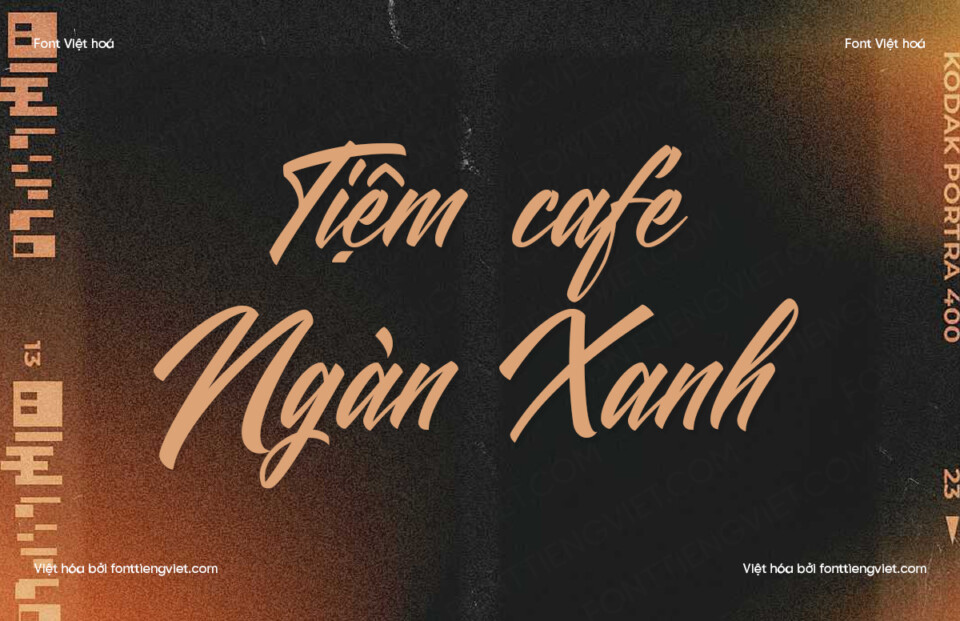
Font Việt hóa 1FTV VIP Pastel Trunk
Tải Ngay Font Việt hóa 1FTV VIP Pastel Trunk – Bộ Font Chữ Vintage Đẳng Cấp Cho Thiết Kế
Giới thiệu về Font Việt hóa 1FTV VIP Pastel Trunk
Trong thế giới thiết kế đồ họa hiện đại, việc lựa chọn một bộ Font Miễn Phí chất lượng luôn là ưu tiên hàng đầu của các nhà sáng tạo. Đặc biệt là với Font Việt hóa 1FTV VIP Pastel Trunk, một siêu phẩm mang phong cách cổ điển kết hợp hài hòa với nét hiện đại tinh tế. Đây không chỉ là một phông chữ thông thường mà còn là linh hồn cho những tác phẩm nghệ thuật đòi hỏi sự tỉ mỉ và cảm xúc. Được đội ngũ 1FTV chăm chút kỹ lưỡng, bộ font này đã được tối ưu hóa hoàn toàn cho bảng mã Telex giúp người dùng tại Việt Nam dễ dàng sử dụng trên mọi phần mềm từ cơ bản đến chuyên nghiệp. Sự xuất hiện của 1FTV VIP Pastel Trunk đã giải quyết bài toán thiếu hụt các font chữ vintage có hỗ trợ tiếng Việt đầy đủ hiện nay.
Đặc điểm nổi bật của Font Việt hóa 1FTV VIP Pastel Trunk
Phong cách thiết kế Pastel độc đáo
Đúng như tên gọi của mình, bộ font này mang đến một cảm giác nhẹ nhàng, dịu mắt như những tông màu Pastel trong hội họa. Các đường nét của Font Việt hóa 1FTV VIP Pastel Trunk được bo tròn mềm mại nhưng vẫn giữ được cấu trúc chắc chắn của những chiếc rương gỗ cổ điển (Trunk). Điều này tạo nên một hiệu ứng thị giác cực kỳ ấn tượng, vừa gợi nhớ về những kỷ niệm xưa cũ, vừa mang hơi thở của thời đại mới. Font chữ này cực kỳ phù hợp cho các bạn học sinh, sinh viên khi làm báo cáo, thiết kế slide thuyết trình hoặc trang trí sổ tay điện tử vì tính dễ đọc và thẩm mỹ cao.
Khả năng ứng dụng đa dạng trong thực tế
Không chỉ giới hạn trong các thiết kế đồ họa phức tạp, bộ font này còn tỏa sáng trong nhiều lĩnh vực khác nhau. Bạn có thể sử dụng nó để thiết kế logo thương hiệu, làm thiệp mời đám cưới, hay thậm chí là trình bày các đoạn trích dẫn ý nghĩa trên mạng xã hội. Đối với các dự án thiết kế bao bì sản phẩm thủ công hay thực phẩm organic, 1FTV VIP Pastel Trunk sẽ giúp sản phẩm của bạn trở nên gần gũi và đáng tin cậy hơn trong mắt khách hàng. Việc tích hợp sẵn các ký tự tiếng Việt chuẩn giúp quy trình làm việc trở nên nhanh chóng, giúp bạn tiết kiệm thời gian chỉnh sửa thủ công các dấu câu phức tạp.
Lưu ý khi sử dụng Font Việt hóa 1FTV VIP Pastel Trunk
Tối ưu hóa hiển thị trên các thiết bị
Mặc dù bộ font này có độ chi tiết cao, nhưng nó vẫn đảm bảo khả năng hiển thị rõ nét trên cả màn hình máy tính lẫn thiết bị di động. Để đạt hiệu quả tốt nhất, bạn nên kết hợp font với những tông màu trung tính hoặc màu pastel đồng bộ để tạo nên một tổng thể hài hòa nhất. Trong các văn bản dài, hãy cân nhắc sử dụng font ở các tiêu đề chính hoặc các đoạn nhấn mạnh để tránh làm rối mắt người xem. Một mẹo nhỏ là bạn có thể điều chỉnh khoảng cách giữa các chữ cái (kerning) rộng hơn một chút để tạo cảm giác thoáng đãng và sang trọng cho bản thiết kế của mình.
Kết luận về bộ Font Việt hóa 1FTV VIP Pastel Trunk